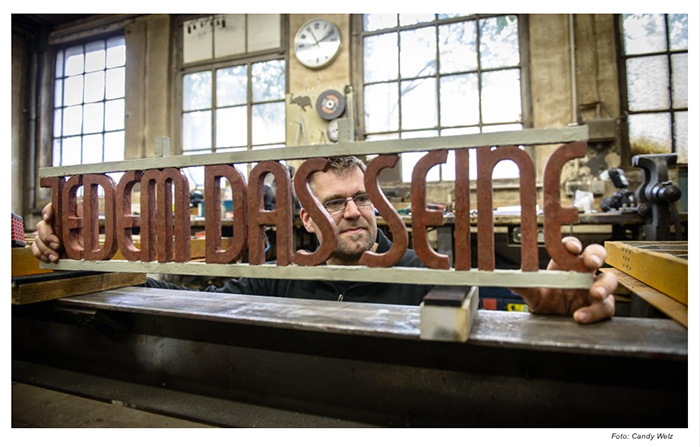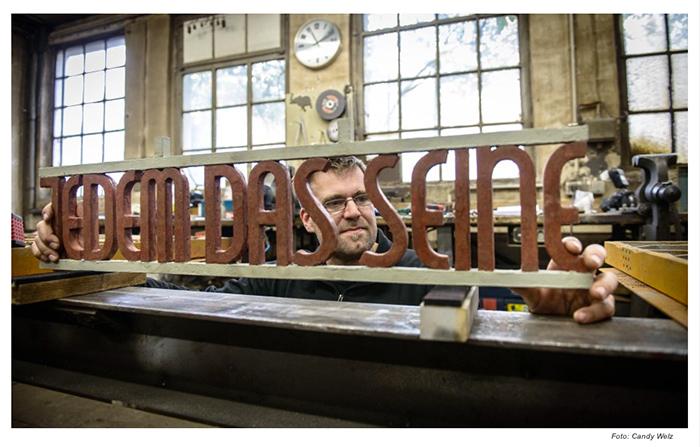
Buchenwald, Franz Ehrlich und der Schriftzug »Jedem das Seine«
Unheimlicher Befund zum Lagertor von Buchenwald
Das Tor des ehemaligen NS-Konzentrationslagers Buchenwald ist wiederhergerichtet worden. Bei der berüchtigten Inschrift "Jedem das Seine" stieß ein Restaurator auf eine verstörende Geschichte. (von Claus Christian Malzahn)
Die Schrift ist schon sehr bauhäuslerisch, das runde A klebt ja auch am Dessauer Haus außen dran. Daß die die Nation überwinden wollenden Nationalsozialisten (Weltherrschaft war das Ziel, und Rasse stand über der Nation) und das Bauhaus so unvereinbar waren, stimmt natürlich nicht. Daß das immer noch wie aus der Gebetsmühle geleiert wird, ist ermüdend. Mir wird in dem Artikel nicht klar, worin außer in dem roten Anstrich der »unheimliche Befund« besteht. Das ist doch alles lange bekannt.
Ja, den »unheimlichen Befund« finde ich auch ausgesprochen reißerisch. »Überraschend« oder »unerwartet« hätte es wohl besser getroffen.
Danke, interessant! Die Schrift differiert beim E und beim N leicht, bei Schmidt hatte Letzteres keinen Sporn. Das führt mich zu einer anderen Frage: Wann wurde eigentlich die erste Unikamerale entwickelt? Lässt sich das sagen?
Daß die die Nation überwinden wollenden Nationalsozialisten (Weltherrschaft war das Ziel, und Rasse stand über der Nation) und das Bauhaus so unvereinbar waren, stimmt natürlich nicht.
Was stimmt daran "natürlich nicht"?
Ich nehme an, Martin meint die Schnittmenge im Antikonservativismus, das jeweilige Selbstverständnis, revolutionäre Modernisierungskraft zu sein, die das bürgerliche Deutschland ablehnt und hinter sich läßt, wenn auch bei deutlich verschiedener Wahl der Mittel.
bei dem Titel mit »unheimlichen Befund« hätte ich erwartet, dass der Schmied, der den Schriftzug renovierte, unter den Lackschichten einen in die Buchstaben gravierten Text gefunden hat. Etwa: "Nach 12 Herrschaftsjahren werdet auch Ihr das Eure bekommen"
Ich nehme an, Martin meint die Schnittmenge im Antikonservativismus, das jeweilige Selbstverständnis, revolutionäre Modernisierungskraft zu sein, die das bürgerliche Deutschland ablehnt und hinter sich läßt, wenn auch bei deutlich verschiedener Wahl der Mittel.
Absolut. Man muß sich die revolutionären Blöcke anschauen, die von Bauhausleuten als Wohnhäuser unter dem Stichwort sozialer Wohnungsbau in die ganze Welt gesetzt wurden. Monumentale Platten für die Massen. In diesem Geist entstand auch so was wie die Ferien-Häuser für Arbeiter in Prora, die später folgerichtig Kasernen wurden. Tom Wolfe hat ein (von Harry Rowohlt übersetztes) Buch über den Einfluß des Bauhauses auf die internationale Architektur geschrieben: Mit dem Bauhaus leben. Recht lustig.
"Die deutlich verschiedene Wahl der Mittel" war für diverse Bauhäusler in der Nazizeit gar nicht so lustig - da haben auch keine "Schnittmengen im Antikonservativismus, das jeweilige Selbstverständnis, revolutionäre Modernisierungskraft zu sein, die das bürgerliche Deutschland ablehnt" geholfen.
Gerade angesichts des Ausgangspunktes dieser Debatte - eines Bauhäuslers im KZ - finde ich diese Formulierungen schon gelinde gesagt sehr unglücklich. Und eine Verbindungslinie Bauhaus - sozialer Plattenwohnungsbau - Kasernen zu ziehen ist in dieser undifferenzierten Vereinfachung ähnlich intelligent wie wenn man Gutenberg für die Veröffentlichung von "Mein Kampf" verantwortlich machen würde.
Natürlich nicht lustig. Aber es gab nun einmal im Bauhaus gewisse sozialistische Tendenzen, und auch Ehrlich selbst war ja nicht nur Bauhäusler, sondern auch Kommunist. Daß andere Sozialisten von den Nationalsozialisten nicht als Antagonisten, sondern als Konkurrenten verfolgt wurden, setze ich jetzt mal voraus (abgesehen davon, daß man wohl unvermeidlich die Grenzen der Forenordnung tangieren würde, wollte man das hier en detail ausdiskutieren).
Aha. Also die Sozialisten (nur die mit Parteibuch oder auch die ohne?) am Bauhaus wurden als Konkurrenten verfolgt - was natürlich einen gewaltigen Unterschied zur Verfolgung von Antagonisten macht. Aber egal wie - offenbar waren sie dann doch nicht so vereinbar mit den Nazis?
Während das "restliche(?)" (nunmehr unsozialistische?) Bauhaus aufgrund der oben erwähnten angeblichen Schnittmengen sozialistischer und nationalsozialistischer Geisteshaltung (?) trotzdem - und das sogar "natürlich" (!) - mit dem Nationalsozialismus laut Martin vereinbar blieb ...
Blöd nur, dass sowohl die Nazis und als auch das Bauhaus selber das ganz anders gesehen haben.
Man muss ja das Bauhaus nicht mögen, aber mit derart konstruierten Nazivergleichen sollte man es dann doch nicht diffamieren. Und selbst rein formale Parallelen zwischen Bauhausarchitektur und Naziarchitektur oder Bauhausdesign und Nazidesign (falls es soetwas überhaupt gab) hinken doch sehr. Letztlich findet man zwischen allem ein kleinstes gemeinsames Vielfaches und wenn es nur die ökonomischen Zwänge im sozialen Wohnungsbau sind. Die Nazis und das Bauhaus haben gleichermaßen Häuser mit Dächern und Türen gebaut! Und haben Teekannen produziert, aus denen Tee getrunken wurde!
Man sollte schon genauer hinsehen und differenzieren, bevor man solch spektakuläre Behauptungen aufstellt - auch wenn diese gelegentlich meist amerikanischen oder englischen Autoren aus ziemlich durchsichtigen Gründen recht flott aus der Feder triefen.
Und jetzt kommt mir bitte nicht mit dem einen oder anderen Bauhäusler, der dann doch irgendwann mit den Nazis gekungelt hat ... die Köpfe und die Masse haben es nicht getan und viele sind daran zugrunde gegangen: durch die Nazis, in der Emigration durch Stalin und auch die vielen Westemigranten und im "inneren Exil" Befindlichen hatten es in den meisten Fällen nicht wirklich leicht. Und das die Nazis nicht jeden Bauhausstuhl verbrannt haben ist wirklich kein Argument dafür, dass sie in irgendeiner Art Gemeinsames mit dem Bauhaus hatten. Weder in der Geisteshaltung noch in der Kunst oder im Design.
Von daher finde ich dass diese Behauptung
Daß die die Nation überwinden wollenden Nationalsozialisten (Weltherrschaft war das Ziel, und Rasse stand über der Nation) und das Bauhaus so unvereinbar waren, stimmt natürlich nicht. Daß das immer noch wie aus der Gebetsmühle geleiert wird, ist ermüdend.
bei aller Wertschätzung für den Kollegen Schröder schon deutlich besser erklärt oder begründet sein sollte, wenn man sie denn schon so lapidar hinwirft und mit dem zweiten Satz auch noch bekräftigt, als wäre das eine fundiert bewiesene Tatsache. Mit Rassentheorien hatte das Bauhaus nichts am Hut. Die Weltherrschaft - im Design - wäre zwar zeitweise fast geglückt, aber eben unfreiwillig: weil die Nazis die Bauhäusler in alle Welt vertrieben.
Und dass die Nazis "Bauhausdesign" (welches ich nicht mal als solches gedeutet hätte, sondern eigentlich eher als etwas sachlichere Ausläufer von Jugendstiltypo angesehen hätte) am KZ-Tor duldeten (bzw. wahrscheinlich gar nicht wahrnahmen) kann natürlich schon gar nicht Begründung  für diese Behauptung sein.
Nach §5 Abs. V der Nettiquette-Regeln sollten wir das nicht hier ausdiskutieren. Ich möchte nur ganz sachte und unscharf andeuten, daß es Parallelen zwischen verschiedenen Modernisierungs- und Revolutionsbewegungen dieser Zeit gab, womit ich allerdings keinen Mord relativieren will, auf gar keinen Fall. Wenn Gutenberger und ich uns mal wieder über den Weg laufen, können wir das unter Zusammenraffen unseres nicht unerheblichen Gelassenheitspotentials bei einem schönen Getränk ein wenig ausführen. Falls wir dann noch Lust dazu haben.
Man muss ja das Bauhaus nicht mögen, aber mit derart konstruierten Nazivergleichen sollte man es dann doch nicht diffamieren.
Ich hatte auch nicht den Eindruck, daß das die Zielsetzung von Martins Nebensatz war. Von meinen Erklärungen auch nicht; auch bin ich kein grundsätzlicher Bauhaus-Gegner. Das ist wie mit Äpfeln und Birnen. Man darf sie ruhig zuzeiten vergleichen, um sich Gemeinsamkeiten und Unterschiede zu vergegenständlichen (oder, wenn Dir Äpfel und Birnen zu nah sind, dann meinethalb Äpfel und Kokosnüsse). Aber man muß das dabei nicht so zuspitzen.